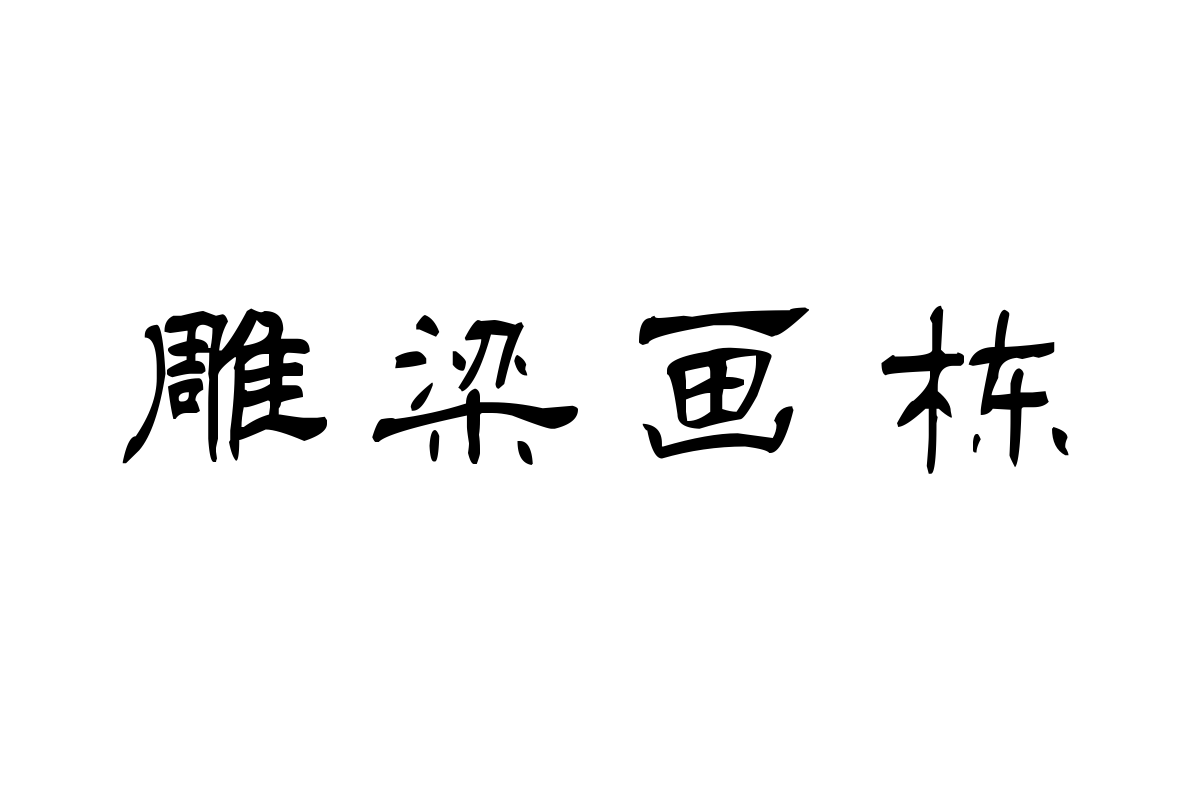
汉呈王天喜隶书是现代书法家王天喜的书法作品之一,以其独特的风格和韵味受到了广泛的关注和赞誉。
王天喜的隶书作品以简洁明快、刚劲有力为主要特点,线条流畅,结构严谨,富有力度感和动感。他的隶书作品在形式上追求简约而不简单,注重线条的表现力和结构的合理性,体现了他对传统书法艺术的深刻理解和独特见解。
此外,王天喜的隶书作品还注重笔墨的变化和运用,通过不同的笔法和墨色来表现汉字的形态和内涵,使作品具有很高的艺术价值和观赏性。他的隶书作品在继承传统的同时,也融入了现代审美观念,展现出了新时代书法艺术的新风貌。